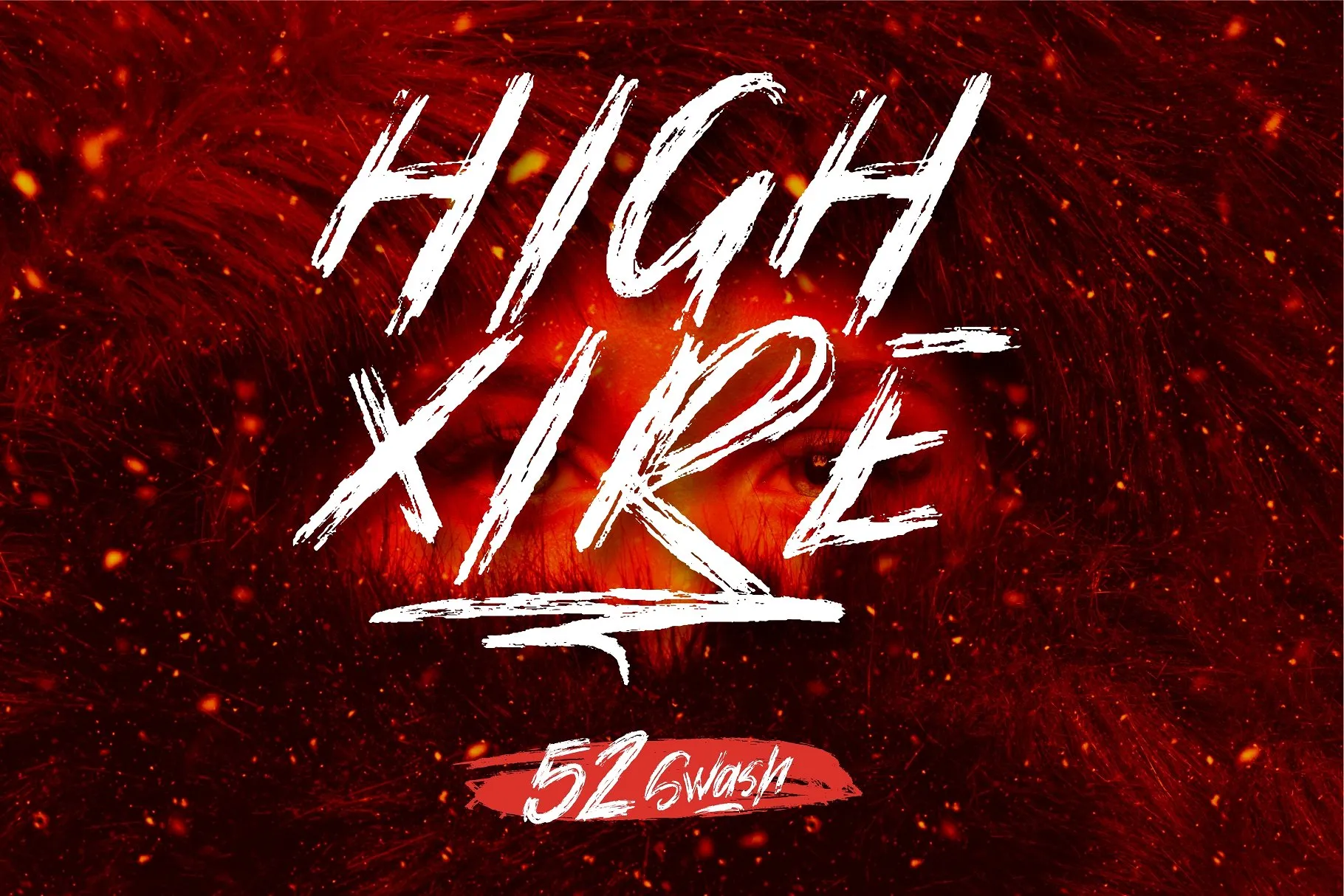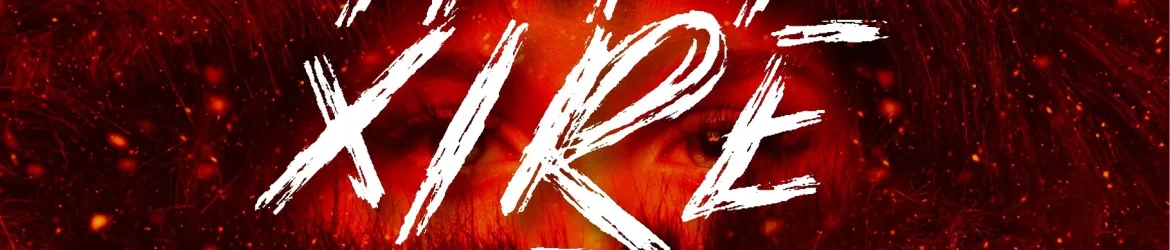
A High Xire Font é uma nova tipografia para uso com ferramentas de desenho livre, criada para aqueles que buscam uma mistura de elegância com um toque urbano e contemporâneo. Esta fonte combina belas curvas artísticas com um sabor moderno que oferece um estilo sofisticado capaz de enriquecer significativamente qualquer projeto gráfico. Seja no design de logotipos, imagens corporativas ou em cartões de aniversário criados à mão, a High Xire é uma escolha ideal para aqueles que desejam dar um toque especial aos seus trabalhos. E se você estiver buscando um estilo único para suas embalagens de produtos ou postagens nas redes sociais, esta fonte pode ser a solução perfeita. Adicione-a à sua coleção de fonts e inspire-se com este novo recurso criativo.